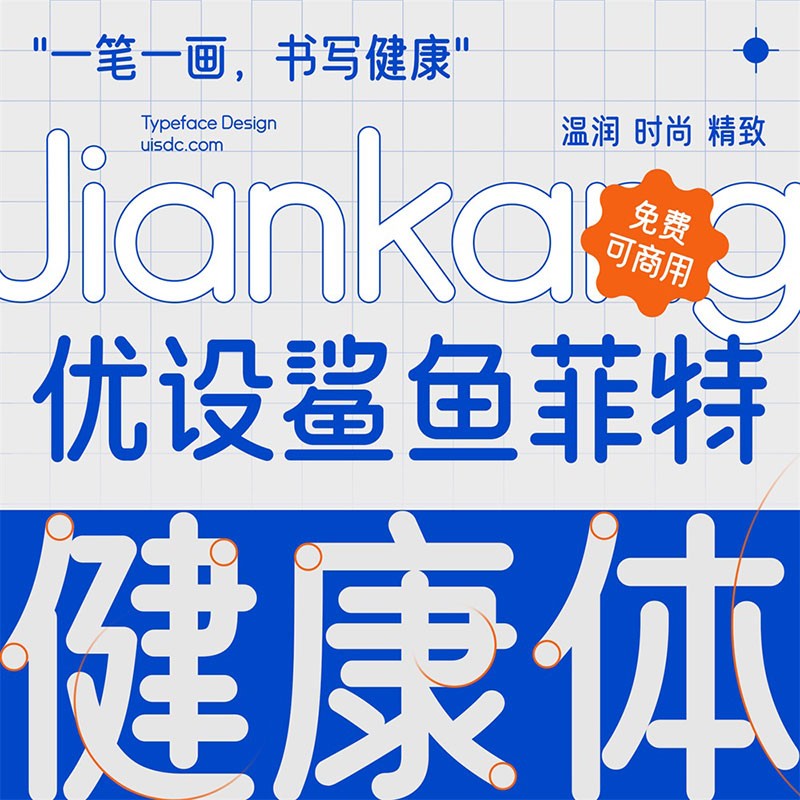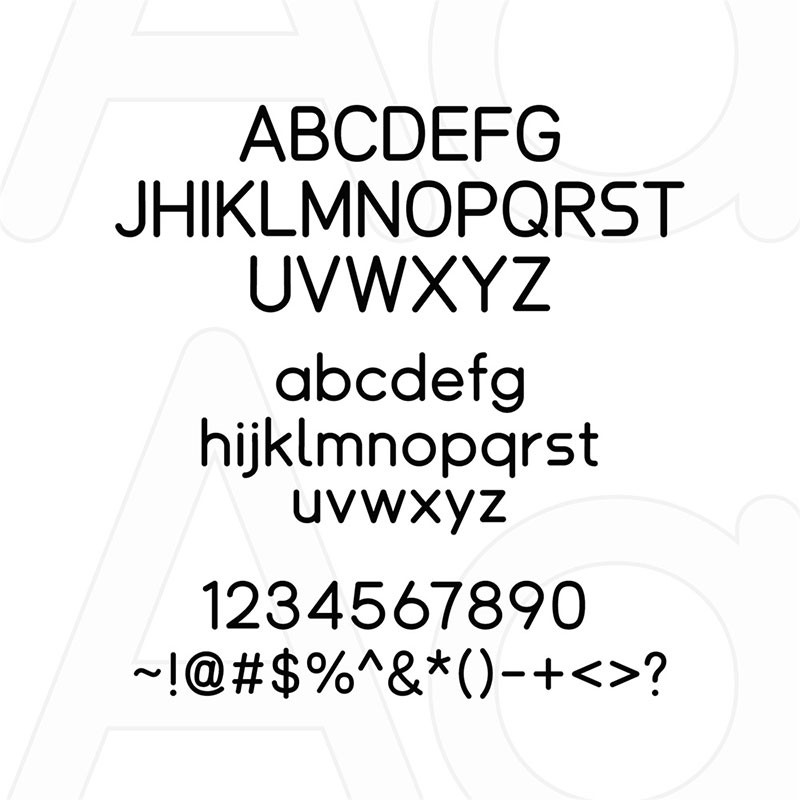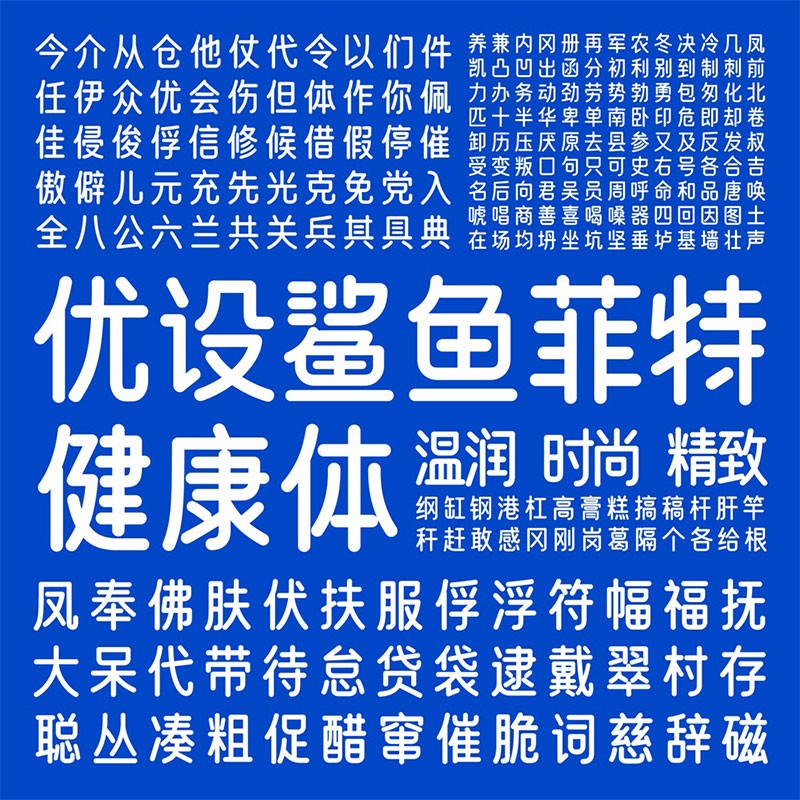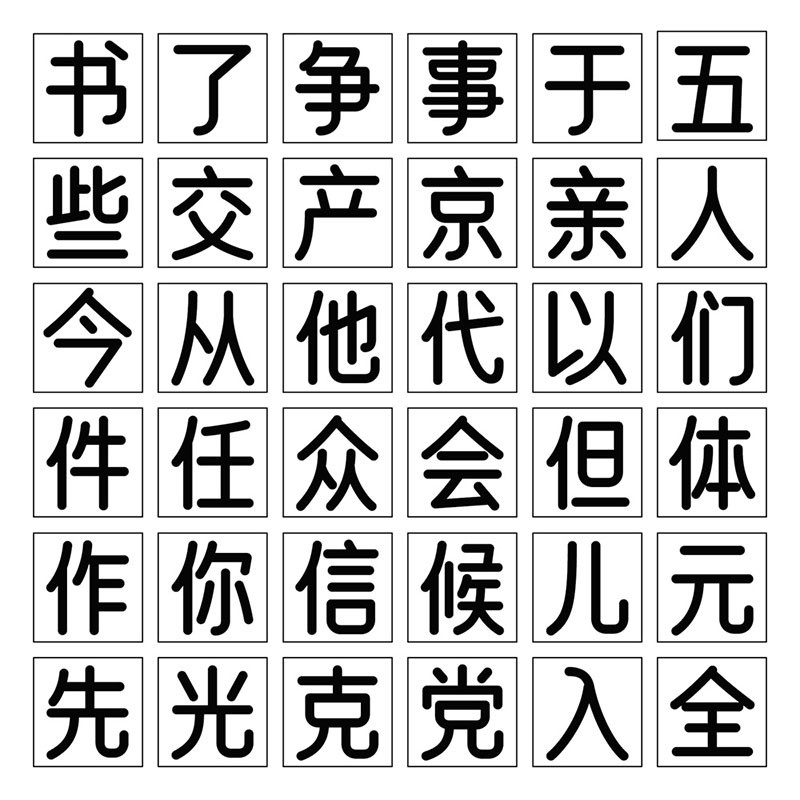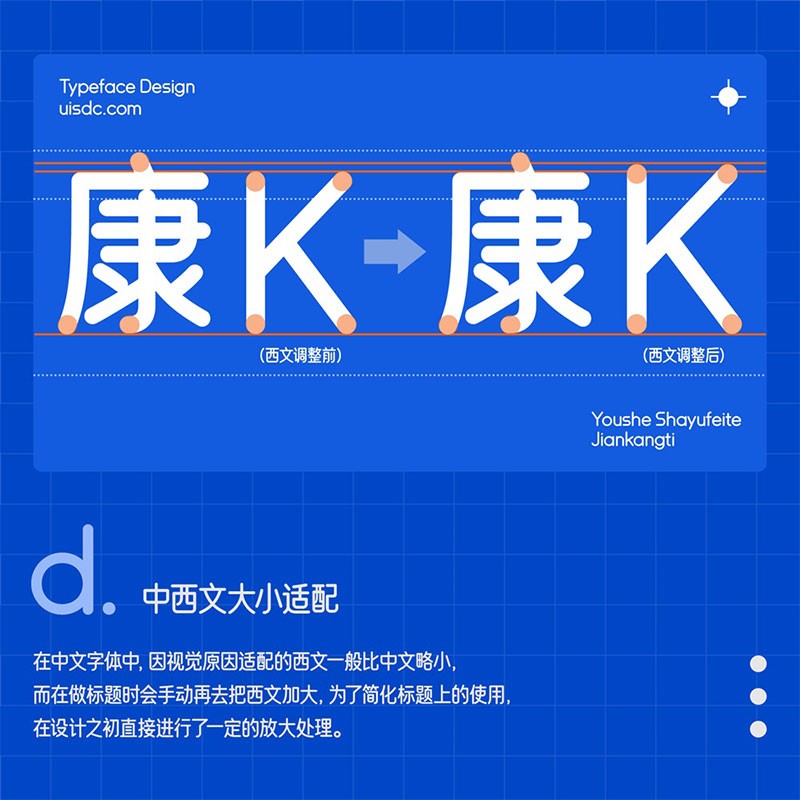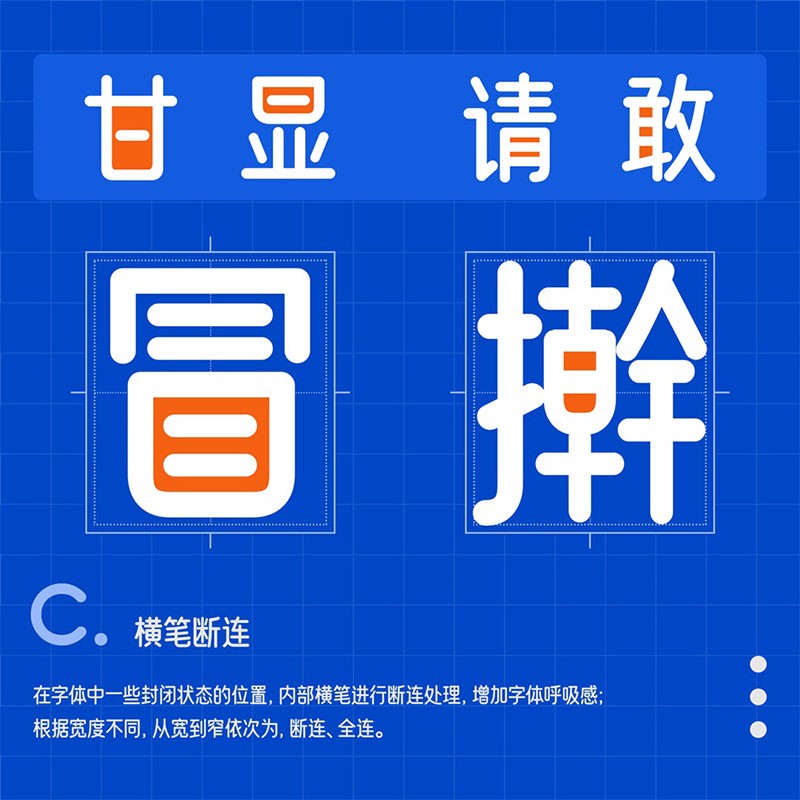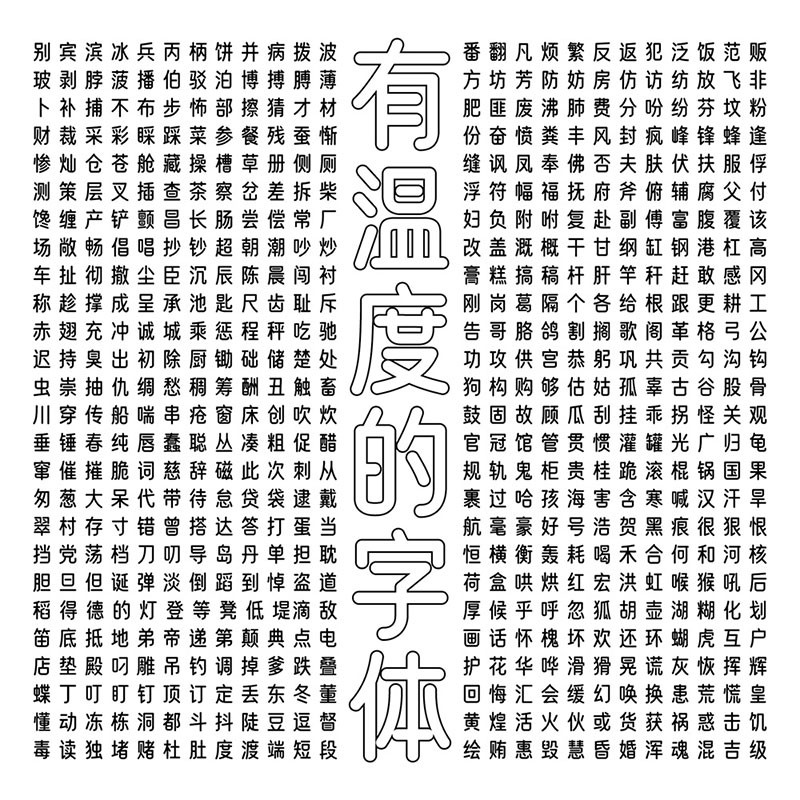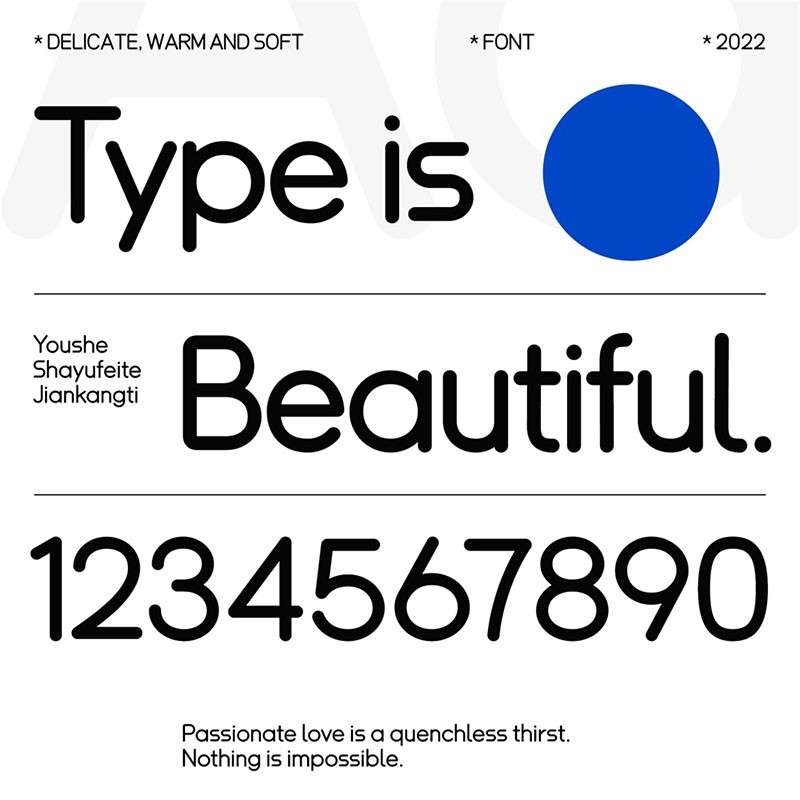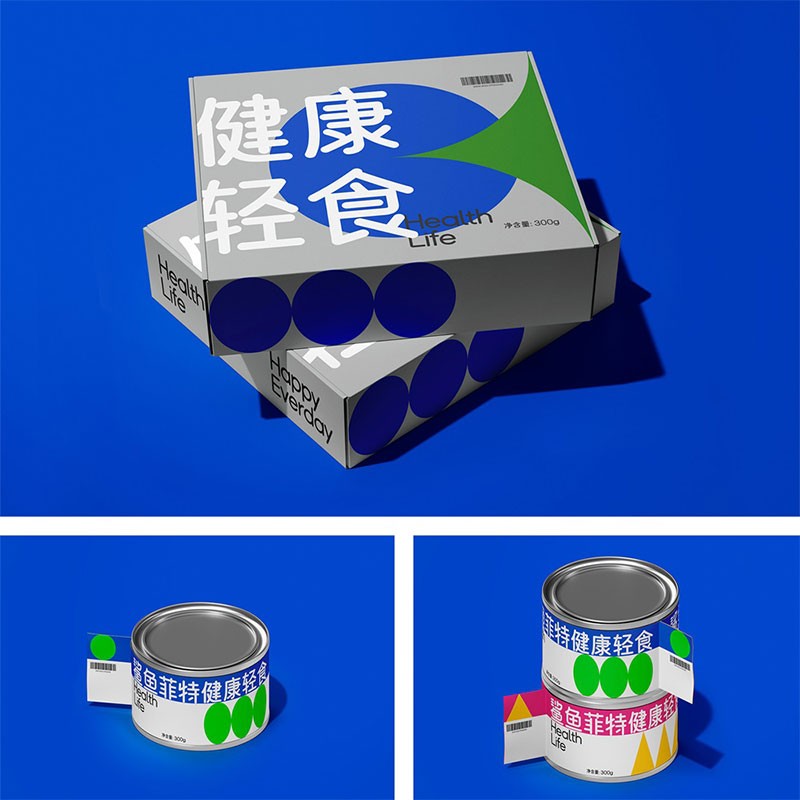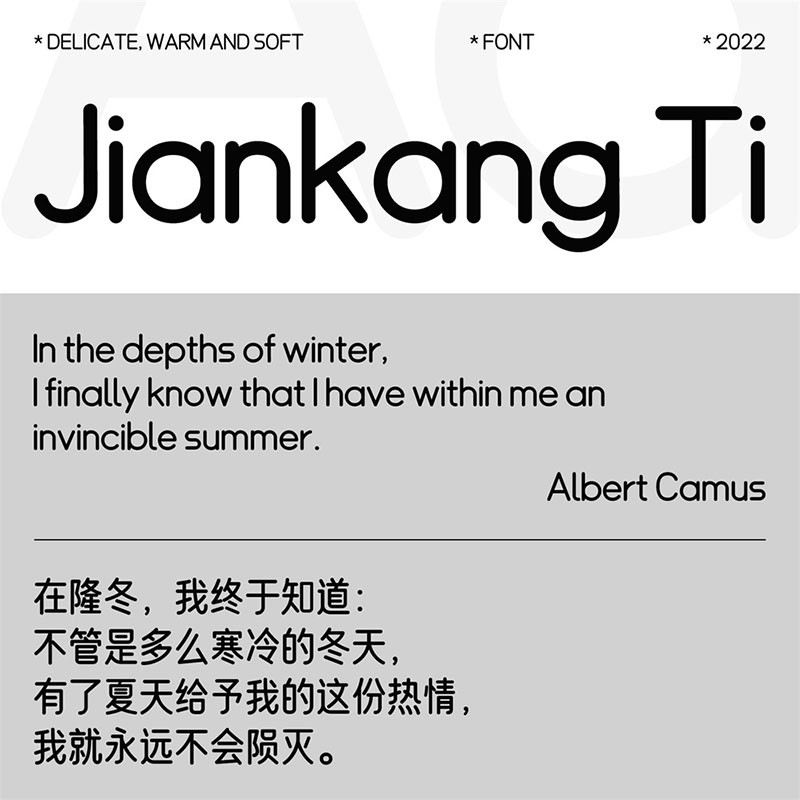
2023年,鲨鱼菲特品牌迎来了5周年!全新品牌定制字体结合“创新健康食品,创造美好生活”的品牌使命创作而成。“优设鲨鱼菲特健康体”正式上线。为了提升品牌字体辨识度与专属性,更好地向用户传递“更少负担,更多选择”的品牌理念与产品价值,鲨鱼菲特联合优设及字由打造了鲨鱼菲品牌专属字体——优设鲨鱼菲特体。
字体将应用于鲨鱼菲特品牌旗下各类业务,线上线下多场景的品牌宣传中。同时为健康轻食领域贡献一款免费可商用的行业标准字体,推动轻食行业蓬勃发展。